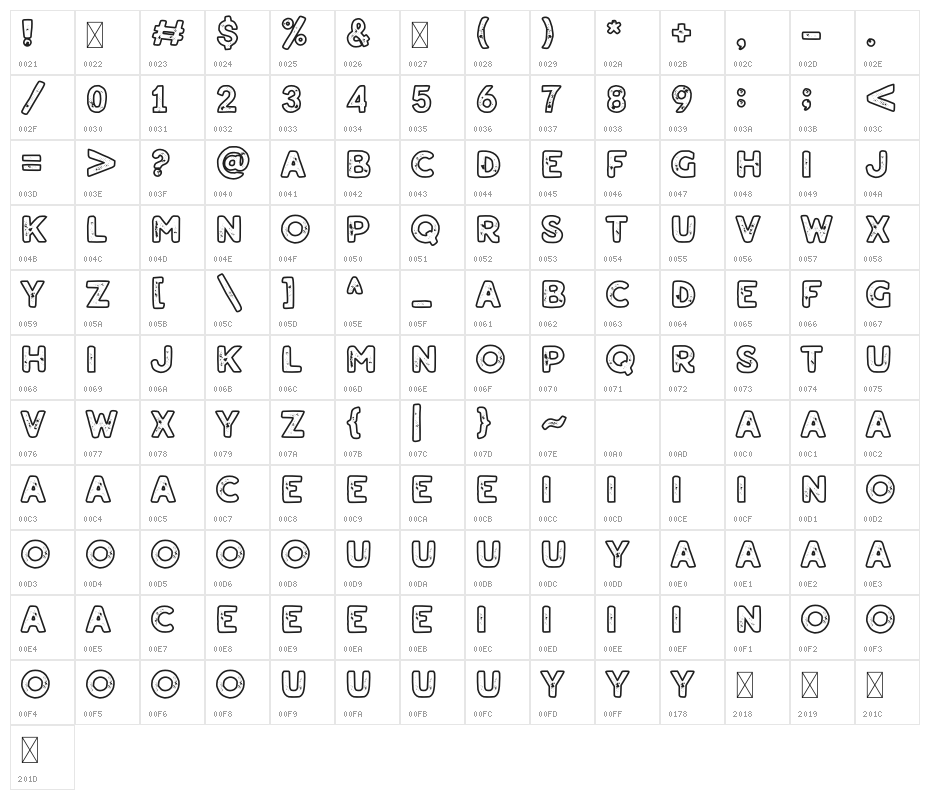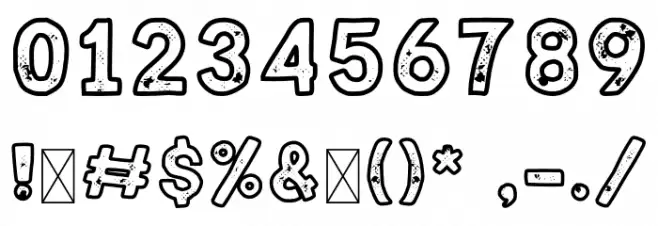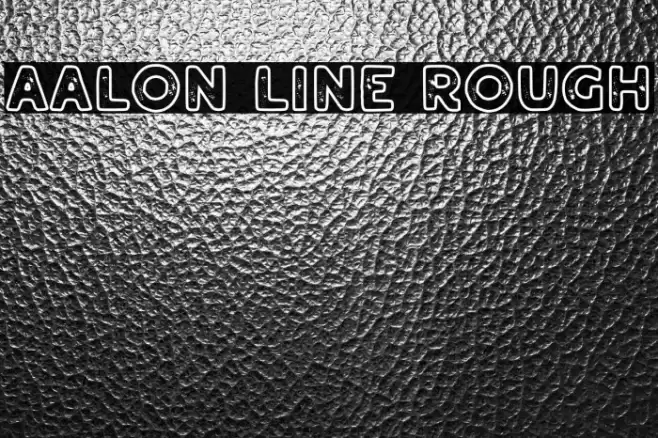
Aalon Line Rough Font
| Proiecte propuse | Ideal for vintage-themed posters, logos, branding, and packaging designs that require a handcrafted or rustic touch. |